今回は、『活字礼讃』を紹介します。
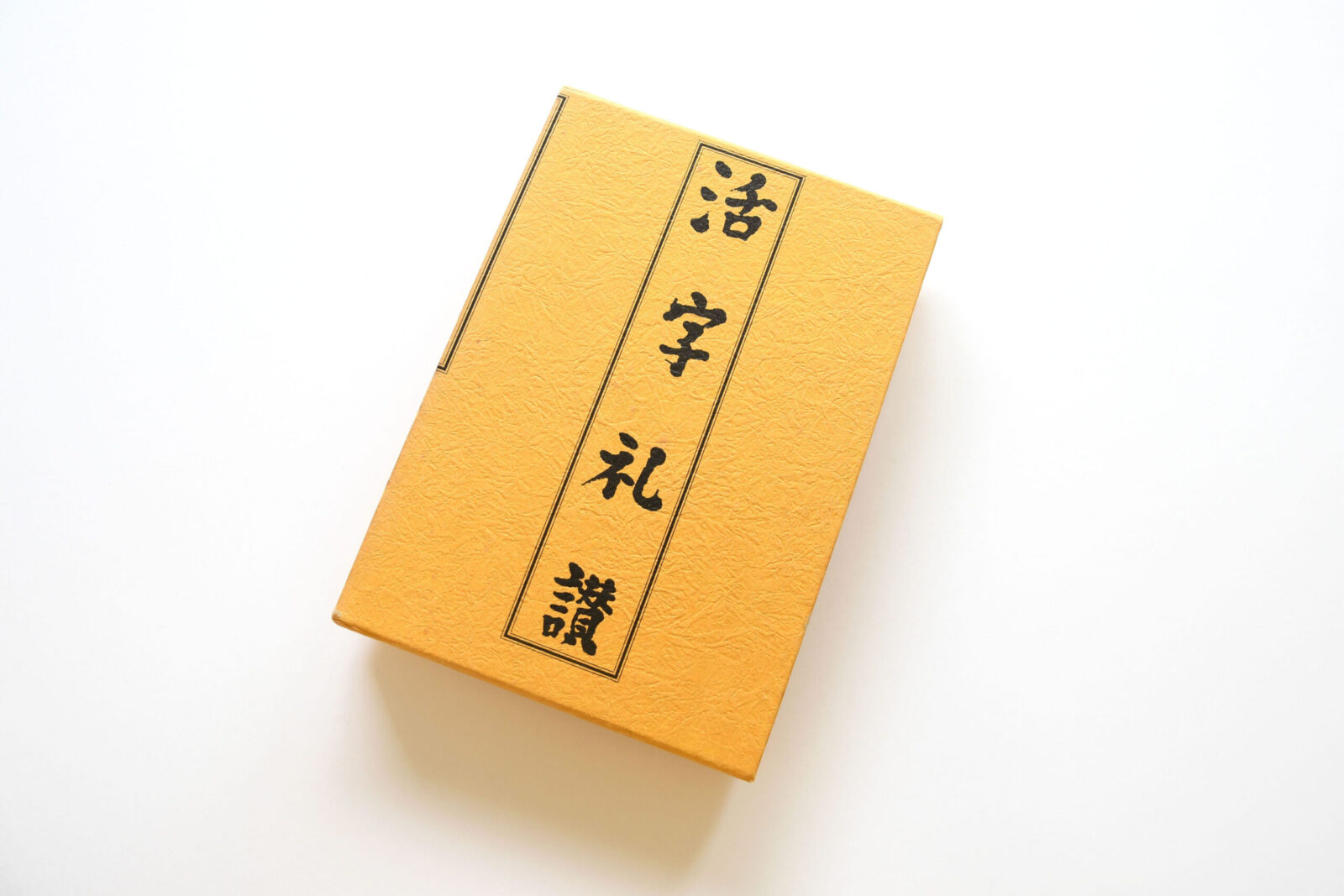
本書は26人の、編集者、デザイナー、活字研究家、作家などさまざまな著名人による活字文化に関するエッセイ集です。
本書のタイトルから、情緒的な文章で活版印刷を称揚したり懐かしむものなのでは…と、どきどきしながら読み始めましたが杞憂でした。金属活字と写植文字、活版印刷とオフセット印刷などを比較しながら、それぞれの優位性や欠点への言及も多くありました。
活版印刷所で文選工として働きながら本を書き、業界の衰退とともに職を変えたという桐生悠三の、文選工としての「わたしの指先からも活字の感触はうすれた。完全に失くなったといっていい。」という実感が伴った一文が印象に残っています。かつては彼のような人の手によるものであった行程の一つひとつが、パソコンに押し込められて見えなくなり、これらの技術や活字文化の移り変わりを経験していない私にとって、そのシステムを理解することはいつも難しく、こういった本によって大きく補われます。
この本の刊行は1991年で、金属活字による印刷が減りつつあった時期です。活字文化の全盛から衰退までを知る人たちによるさまざまな視点で、当時の様子と空気感を知ることができます。